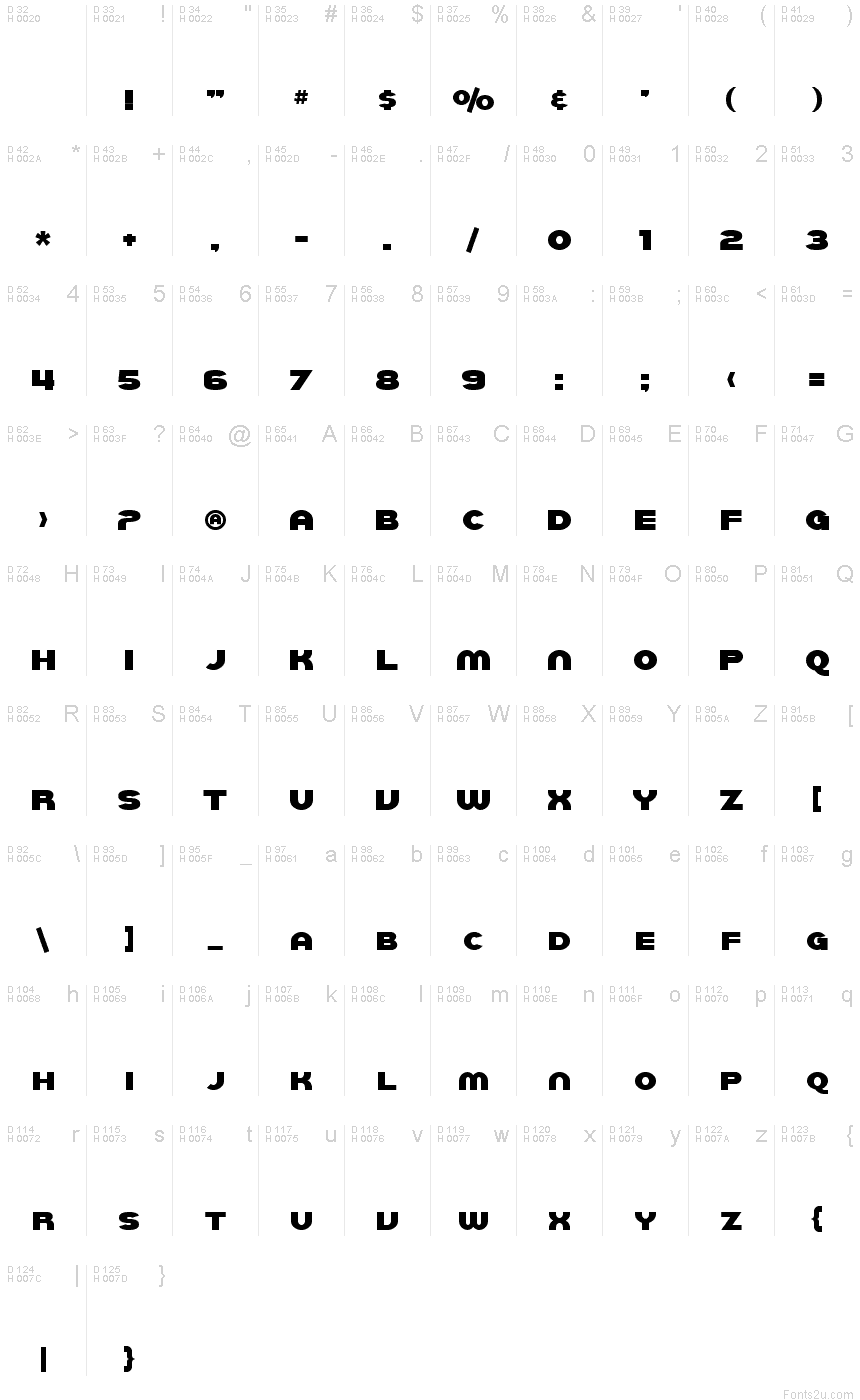
SF Juggernaut od ShyFoundry to bezpłatny, nowoczesny krój displayowy, składający się wyłącznie z wielkich liter, o surowym, futurystycznym charakterze. Litery wyglądają jak wykute z ciężkich, geometrycznych bloków – szerokie łuki, głębokie wycięcia i kanciaste łączenia nadają alfabetowi kompaktowy, sci-fi rytm, nie tracąc przy tym na przejrzystości.
Sprawdzi się w nagłówkach plakatów, oprawie graficznej gier, okładkach płyt, planszach tytułowych i logotypach, wszędzie tam, gdzie potrzebujesz darmowego fontu z konkretną masą i industrialnym sznytem. Grube sylwetki i wyraźne wewnętrzne kształty czynią go świetnym wyborem do monogramów i tekstów na okładki – nawet kilka liter wystarczy, by uzyskać ten muskularny, niemal mechaniczny efekt.
SF Juggernaut
ShyFoundry
Derek Vogelpohl